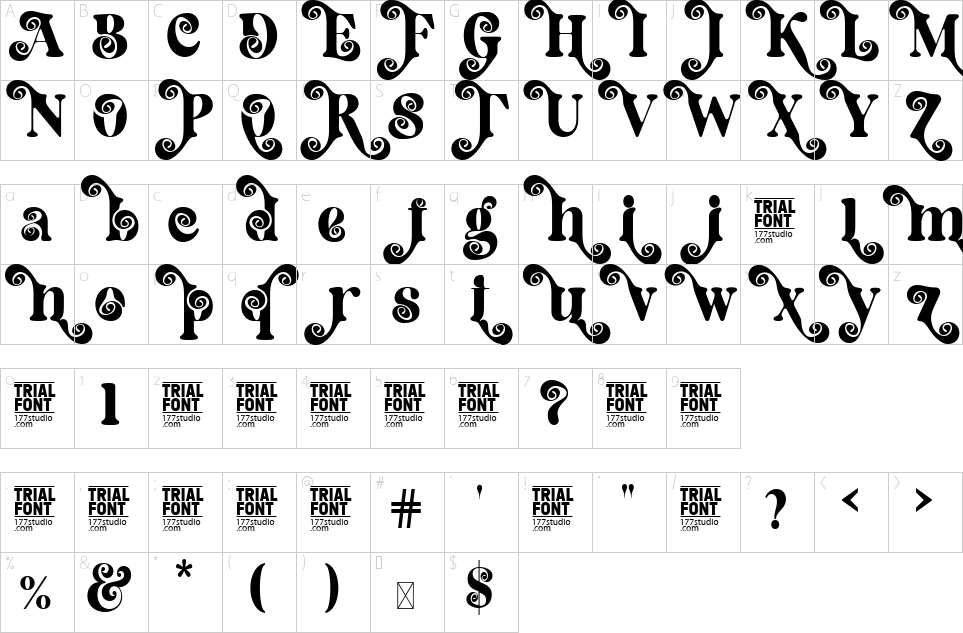
A Dilemma Problem é uma fonte moderna e dinâmica que se destaca no seu ambiente digital, adaptando-se perfeitamente para projetos tanto profissionais quanto não formais. Desenvolvida pelo designer anônimo de 177studio.com, esta fonte pode ser facilmente usada em dispositivos Windows e Mac. Suas linhas fluidas e variedade de gêneros criam um ambiente visual agradável para textos gráficos ou legais, oferecendo uma alternativa elegante e versátil entre outras opções disponíveis no mercado. Com 549 downloads até o momento, esta fonte é uma escolha inteligente para designers que procuram flexibilidade sem comprometer sua estética. Não perca tempo, instale agora a Dilemma Problem em seu próximo projeto e deixe suas criações sofrerem por um novo grau de beleza tipográfica.